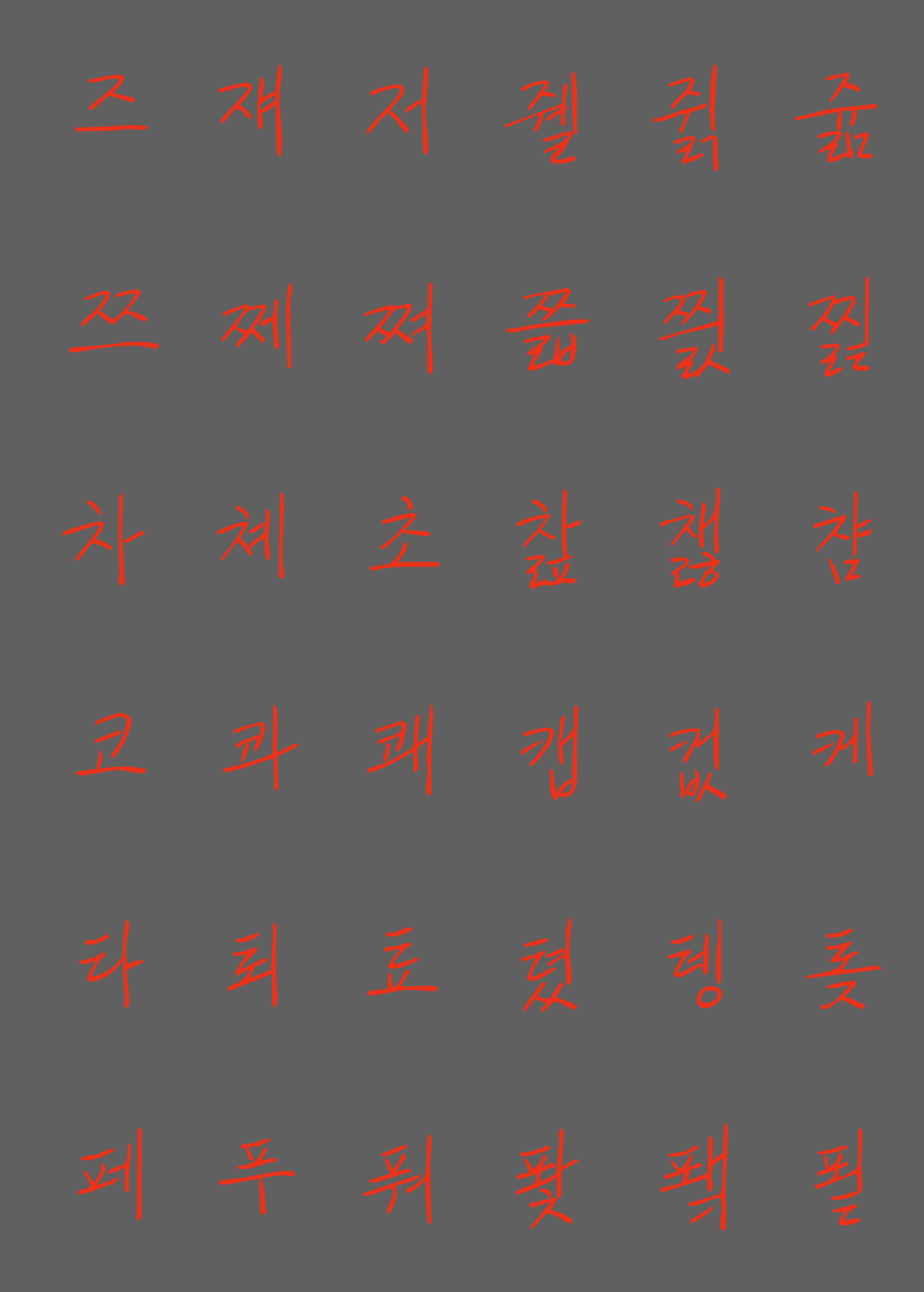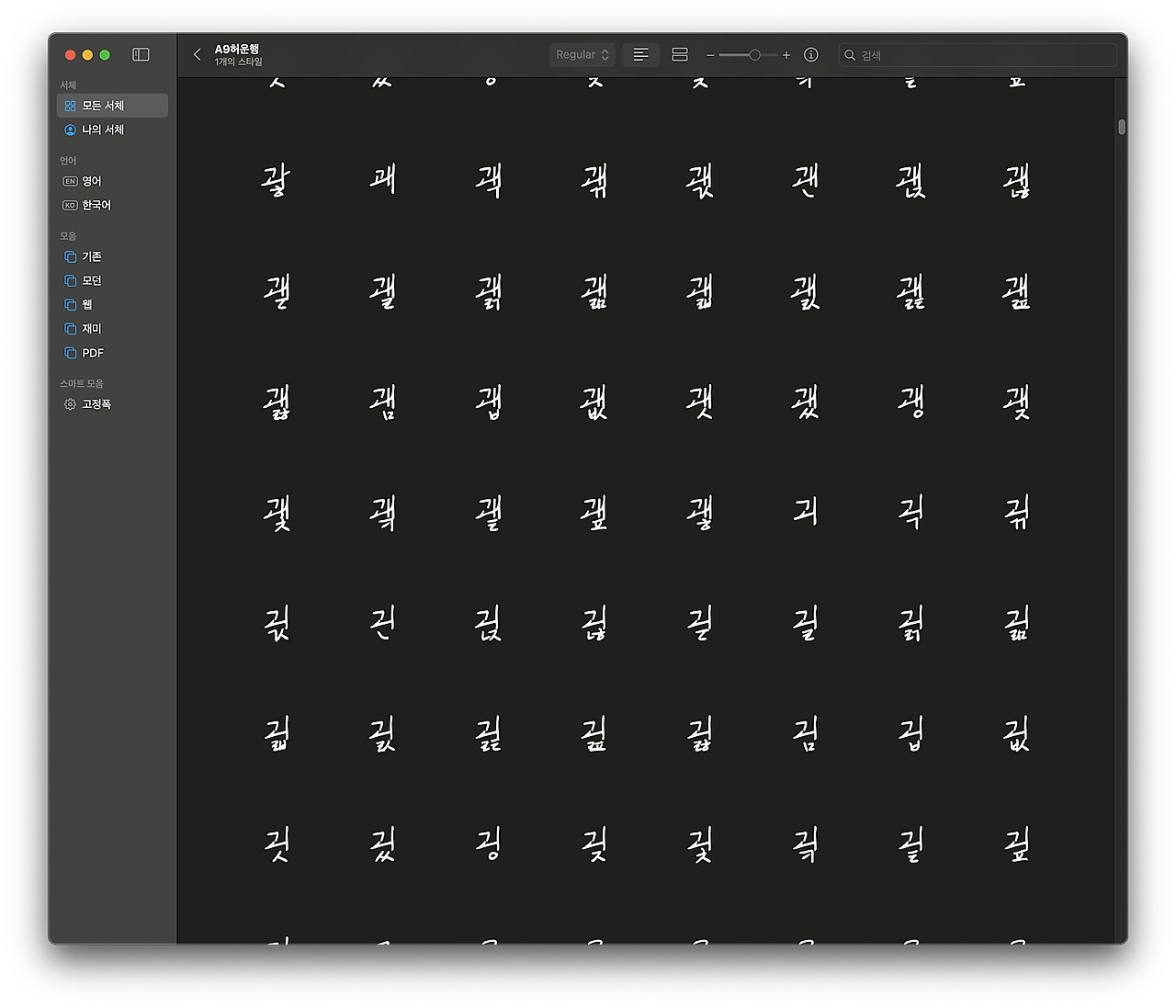
남의 손글씨 폰트를 만들기
주말 반납... 폰트 작업중
개인은 고유의 스타일이 있는데 몇가지 빠진 상태에서 우선 작업을 했는데 그걸 다시 맞춰 보려다 보니 주말을 반납했습니다.
이빨빠진 상태에서 어느정도 결과물은 나오는거 같습니다. 흘려쓰는 느낌이 있는 글자에 이거 하나 맞추면 저게 틀어지는 형태가 되는 부분은 아예 알고리즘을 바꿔서 프로그램 구조를 바꿀 계획입니다.
선순환이란 결국 많은 일을 하면서 좋아지는 것일테니 피드백을 받으면서 계속 수정할 예정입니다. (당분간 기능개선되면 폰트도 개선)
폰트를 초성, 중성, 종성 테이블 별로 전체를 보면서 제작하는 에디터를 현재 일러스트레이터나 벡터기반 프로그램에서 설계할 수 있게 재구성 중입니다. 결합된걸 보면서 제작하는게 효율적이죠 조합의 하나하나도 중요하지만 ^^